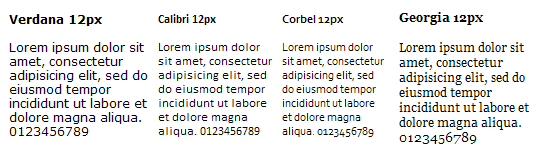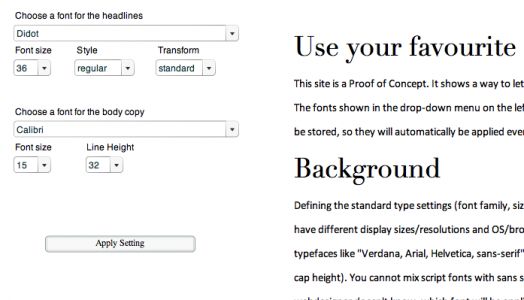
Warum sind die Vista-Schriften so klein?
Im Moment verwende ich für eine Homepage die Schrift Verdana. Beim normalen Text in der Schriftgrösse 12 Pixel (font-size:12px;). Damit die zukünftigen Vista Benützer ihre neuen Schriften auf der Homepage sehen, wollte ich die Calibri in die css-Schriftdeklaration aufnehmen. Erste Priorität = Calibri, zweite Priorität = Verdana (font-family:Calibri, Verdana, Helvetica, Arial;). Somit ändert sich nur etwas wenn die Schrift installiert ist, für die anderen bleibt es bei der Verdana.
Nur, alle serifenlosen Vista-Schriften (Calibri, Candara, Corbel) sind merklich kleiner als die Verdana, Georgia, Arial, etc. Benützt werden lediglich 10 Pixel. Das hat zur Folge das auch die Schriftgrösse überall angepasst werden müsste.
Hat jemand eine Erklärung warum das Microsoft gemacht hat? Für mich ist das nicht logisch.
Somit hat sich Microsoft also selber mit Gebrauch der neuen Schriften vom Homepage-Markt verabschiedet! :lol: (dabei sollen es ja auch Screen optimierte Schriften sein) Es wird wohl niemand eine Vista-Schrift optimierte Homepage ins Netz stellen und in Kauf nehmen, dass bei allen "nicht Vista Benützern" das Layout ziemlich anderst aussieht.
Es wird sich bestimmt ein Javascript Developer finden, der sich diesbezüglich etwas einfallen lässt...
Microsoft scheint einerseits eine sehr traditionsbewußte Firma zu sein. Und man hat das ja schon vor ewigen Zeiten mit Times New Roman und Arial so eimgeführt, daß die wichtigsten Windows-Systemschriften bei gleicher nomineller Punktgröße sehr unterschiedlich ausfallen.
Gleichzeitig legt Mirosoft aber auch Wert darauf, daß Anwender flexibel bleiben. So wurde mit Einführung von Windows 95 der bis dahin links oben plazierte Fenster-Schließknopf (das waren die Anwender von Windows 3.1, vom Atari, vom Mac her seit Urzeiten gewöhnt) nach rechts oben verschoben. Und auch heute noch finden sich viele Menübefehle bei jeder neuen Word-Version an einer anderen Stelle. Warum sollte Microsoft nun nicht auch für Webanwendungen die Flexibilität der Anwender und Programmierer auf die Probe stellen?
Habe gehör, dass die neuen Schriften vor allem die Stärke des teuer entwickelten ClearType Systemes zur Schau stellen sollen ...
Somit wollen die wohl dem Benutzer aufs Auge drücken, dass die Fonts selbst kleiner viel besser zu lesen sind als ihre Vorgänger.
Es wird sich bestimmt ein Javascript Developer finden, der sich diesbezüglich etwas einfallen lässt...
Hab heute mal ein wenig damit rumgespielt:
(Funktioniert nur, wenn Calibri installiert ist, aber momentan noch nicht im IE)
Ich hole über eine Flash-Film die Liste aller installierten Schriften.
Übergebe diese als Array an Javascript.
Vergleiche die Array-Elemente mit dem String "Calibri".
Wenn die Bedingung wahr ist, wird per DOM Scripting der Klassenname des P-Tags auf den Klassenname "cleartype" umgestellt, der dann die Calibri und eine größere Font-Size zuweist.
Wenn man das dann in einem Cookie speichert, könnte man per PHP von Anfang an, die Cleartype-CSS-Klasse für alle Folgeseiten (und Folgebesuche) benutzen.
Wäre doch vielleicht ein tolles Feature für Typografie.info 2.0, wenn jeder Besucher eine beliebige seiner installierten Schriften (einschließlich Wunschgröße) einstellen könnte. :D
Schock?
Warum nicht? Wir brauchen hier doch keinen »Corporate-Look«. Mancher hat hier einen Uralt-PC in der Bleisatz-Ecke stehen, andere einen 24-Zoll-Angentur-Monitor. Die Voraussetzungen sind unterschiedlich, warum dann nicht auch die Darstellungen. Genau da hin wird sich das Web entwickeln …
Naja, zumindest ungewohnt. Wenn ich mal drüber nachdenke, habe ich es aber eigentlich in den meisten Fällen gern, wenn mir diese Entscheidung abgenommen wird. Ich würde im zweifel eher erwarten, ein passendes Design für meine Vorraussetzungen (wie immer die grade sind) geliefert zu bekommen, ich würde nur bei wenigen Seiten (diese hier wäre vielleicht eine der wenigen Ausnahmen), mir die Mühe machen selbst eine Schrift auszusuchen. Was mich am meisten stören würde ist, dass die Wiedererkennbarkeit auf verschiedenen Rechnern nicht gegeben wäre. Es könnt sich keine Gewöhnung einstellen. Vor einigen Jahren gab es ja viele Versuche, die selbe Seite mit einigen unterschiedlichen Layouts zur freien Auswahl anzubieten. Das ist technisch ja längst kein Problem mehr. Es gibt aber wohl Gründe, warum das wieder aufgegeben wurde (oder macht das noh irgenwer?). Ich vermute, dass die meisten Benutzer tatsächlich diese Wiedererkennbarkeit haben wollen, ich schließe mich da nicht aus.
Es wäre natürlich nur eine optionale Einstellung. Natürlich gäbe es trotzdem eine Standardeinstellung.
Diese Wahl-Templates haben sich tatsätlich nicht durchgesetzt, weil sie ja nur ein rein dekoratives Feature waren. Angepasste Schrifteinstellungen hätten aber schon einen echten Nutzen, finde ich.
Alles in allem: Das gefällt mir :)
Und wenn man den Webmaster kennt, kann man ihn sogar bitten, Sonderwünsche zu integrieren :wink:
Hier nochmal die Variante, die alle Schriften zeigt:
Ist aber problematisch, da gerade die Fonts, die wir Designer so auf dem Rechner haben, nicht ins notwendige Windows-Fontfamily-Schema (regular/italic/bold/bold italic) passen, was für den HTML-Aufruf notwendig wäre.